Шрифт в кинематографе
Увлекательная лекция Александра Васина о том, как подбирались шрифты для кино в разные времена, как с их помощью авторы передают дух эпохи или стиль фильма, а также о том, как ляпы и неуместное использование шрифтов могут разрушить образ.
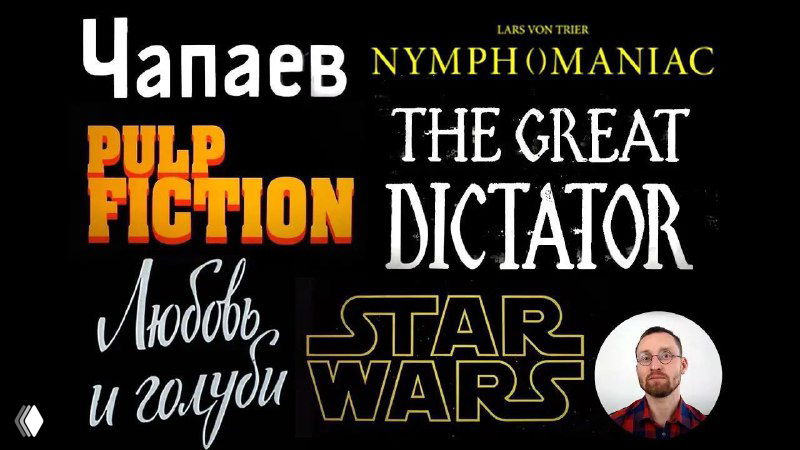
Коллаж из логотипов фильмов и разных шрифтов на тёмном фоне, демонстрирующий разнообразие типографики в кино и визуальный контекст лекции
Коллаж с названиями фильмов и разными стилями шрифтов, иллюстрирующий тему лекции о типографике в кино.